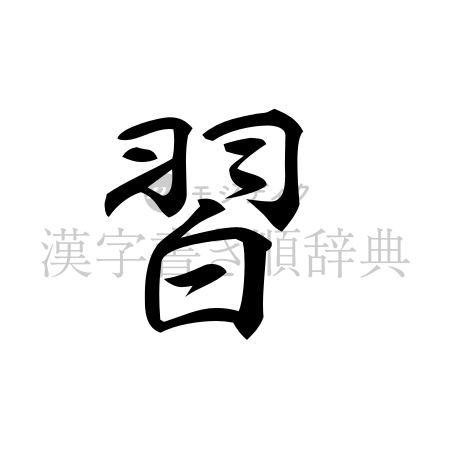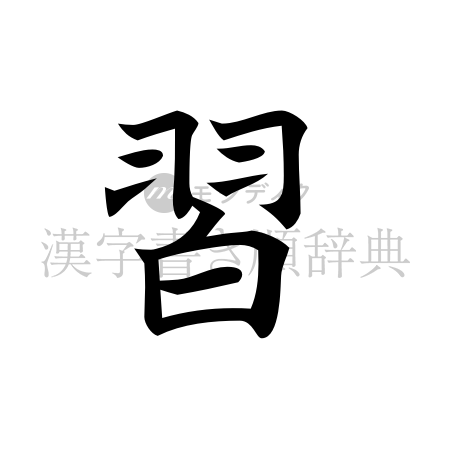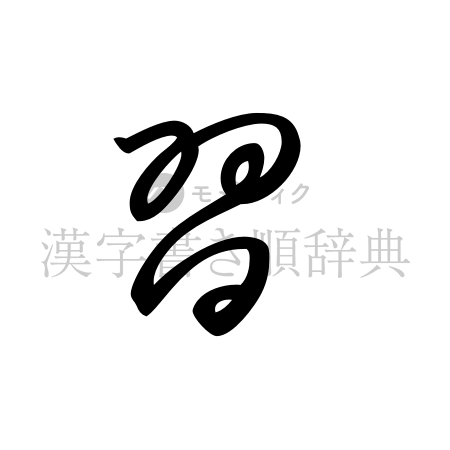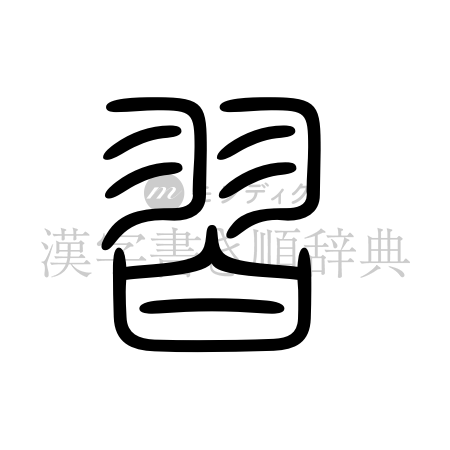
漢字「習」(はねに白)の書き順・読み方・意味・部首・画数
「習」の書き順動画アニメーション(11画)
「習」の書体
• 習の書体「ゴシック体」のイメージ
• 習の書体「明朝体」のイメージ
• 習の書体「教科書体」のイメージ
• 習の書体「楷書体」のイメージ
• 習の書体「行書体」のイメージ
• 習の書体「草書体」のイメージ
• 習の書体「隷書体」のイメージ
• 習の書体「篆書体」のイメージ
「習」の意味
• 学ぶこと。
• 練習すること。
• 慣れること。
• 繰り返し行うこと。
• 鳥が羽ばたくこと。
「習」の意味の英訳
漢字は1文字で多様な意味を持ちますが、「習」を英語で表す場合、一般的には learn などがあります。
「習」の成り立ち・由来
六書分類 会意文字
構造 羽(はね)+日/白(くり返し飛ぶさま)
「羽」と、その下の部分とを組み合わせた会意文字とされます。上部の「羽」は鳥のはねを表し、下部はもと「日」で、日の光のもとを意味したと考えられています。ひな鳥が日ざしの中で何度も羽ばたき、飛ぶことを覚えるさまを示し、そこから「くり返し練習する」「ならう」「なれる」意が生まれました。のちに下部は「白」の形に定まりました。字源には諸説がありますが、「反復して身につける」という中心の意味は古くから一貫しています。
※ 下部を「日」とみる説と「白」を音符とみる説があるなど、字源には諸説があります。
「習」は上に「羽(はね)」、下に「白(しろ)」を組み合わせた漢字です。